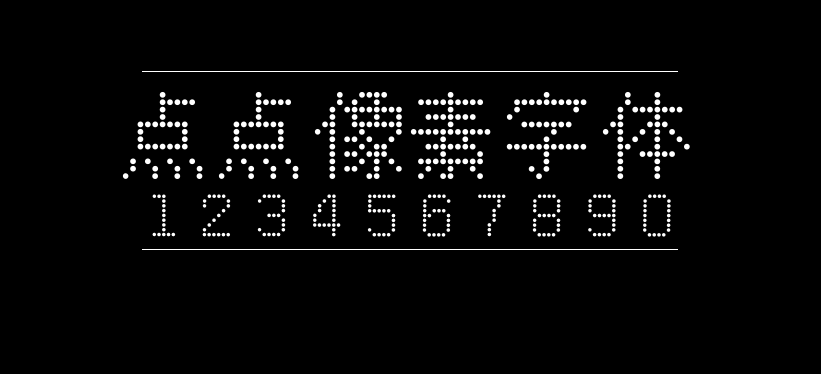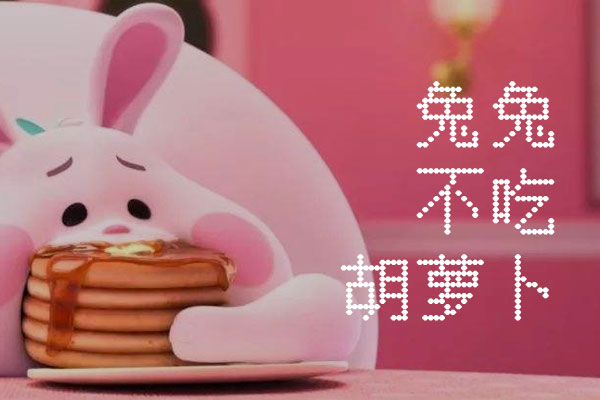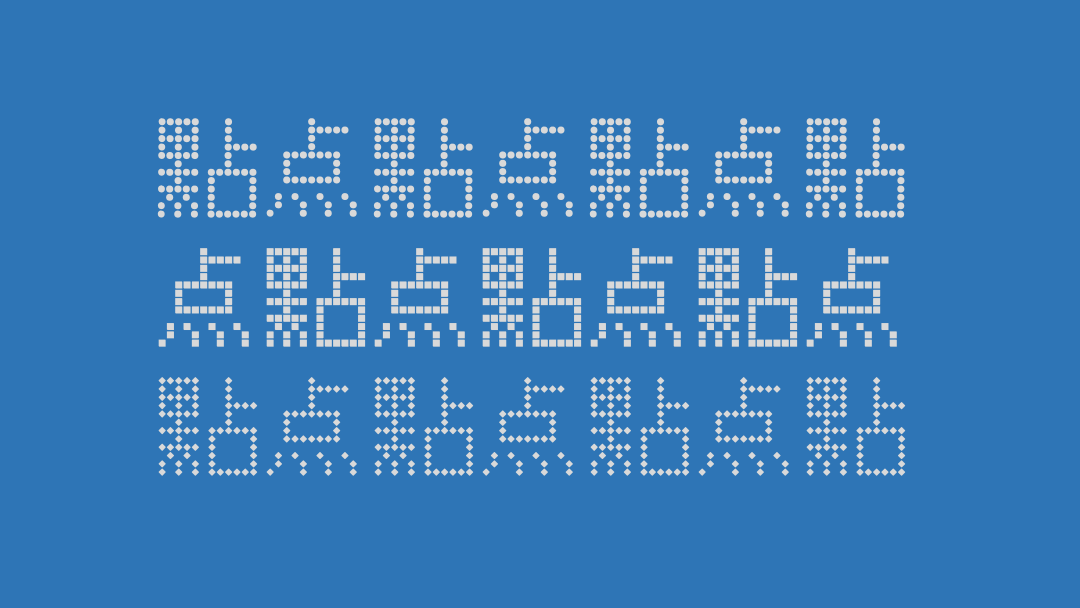
点点像素字体
点点像素字体(Dotted Songti)是一款在Github上免费开源的中文像素艺术字体,基于GPL 2.0协议开源发布,作者是中国大陆的wixette。
该字体包含有3种字型(圆点、方点、菱形点),每种字型均支持超过22000个Unicode字形,覆盖GBK编码中的全部简繁体汉字。在下载的字体文件包中,包括三个字体文件,主要的区别是字体的点的形状不一样。有三个样式,一个是圆形的点,一个是方形的点,还有一个是菱形的点。
目前发布的点点像素字体是基于文泉驿项目所创建的一 种点阵字体衍生而来的。它们是文泉驿点阵宋体经矢量化之后,通过变形、美化而得到的。文泉驿点阵宋体是基于GPL 2.0协议开源的自由字体。作者将文泉驿点阵宋体中的字型矢量化,然后变形加工为不同风格的字体。